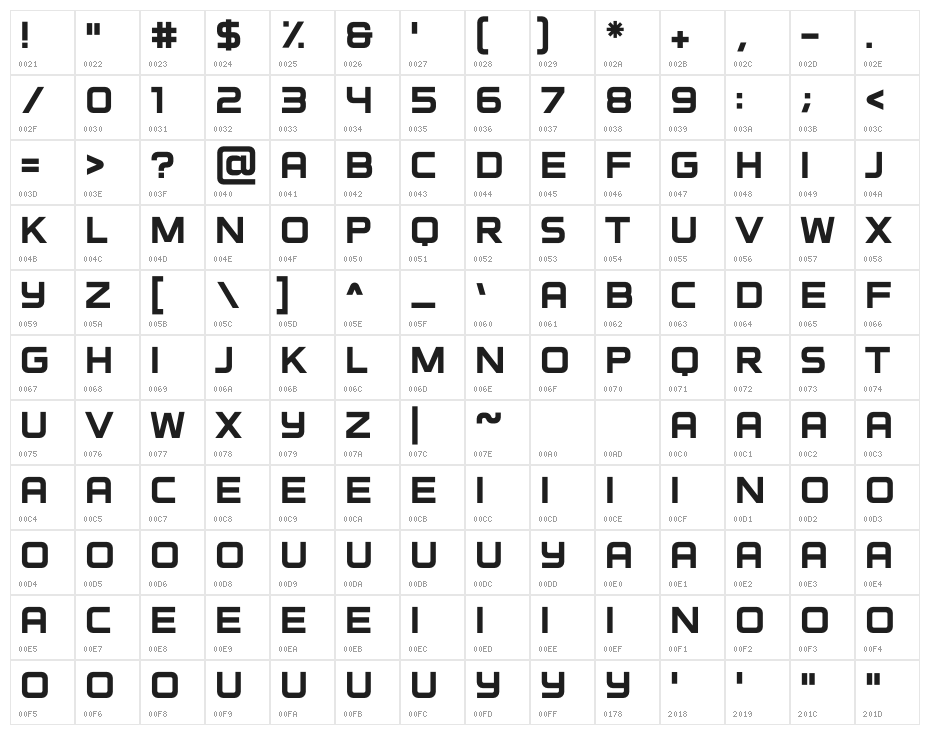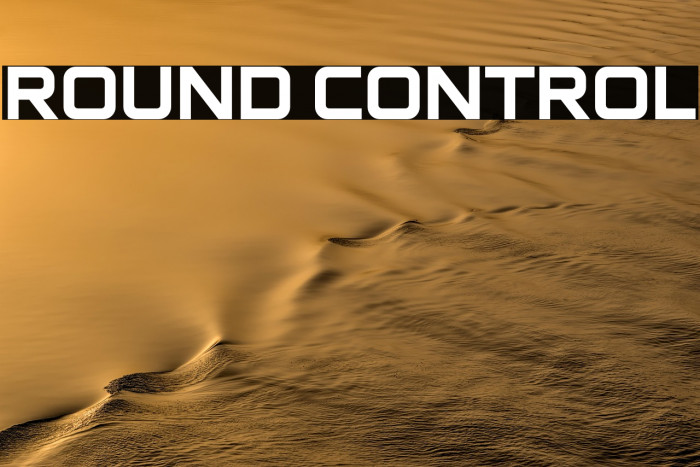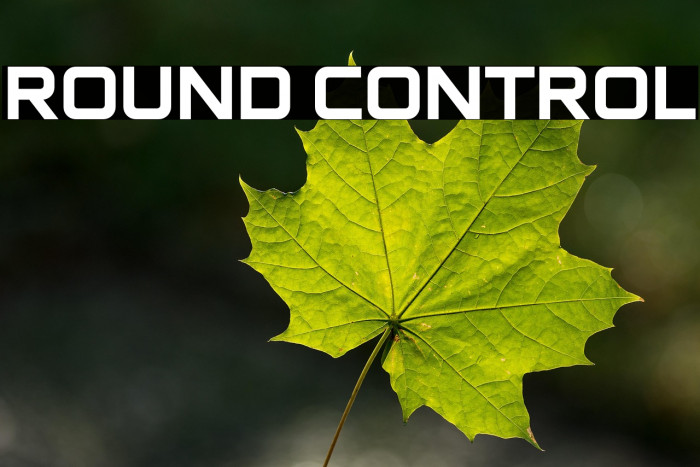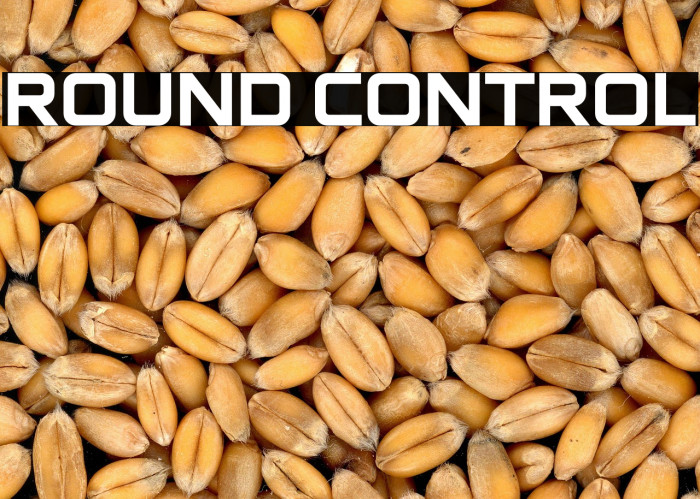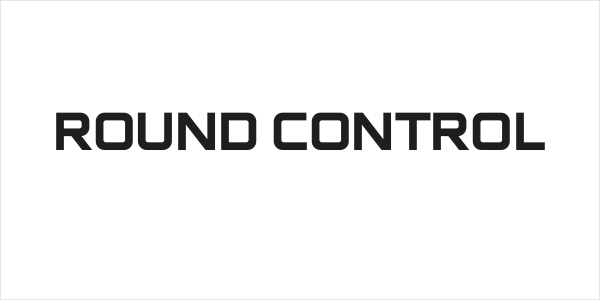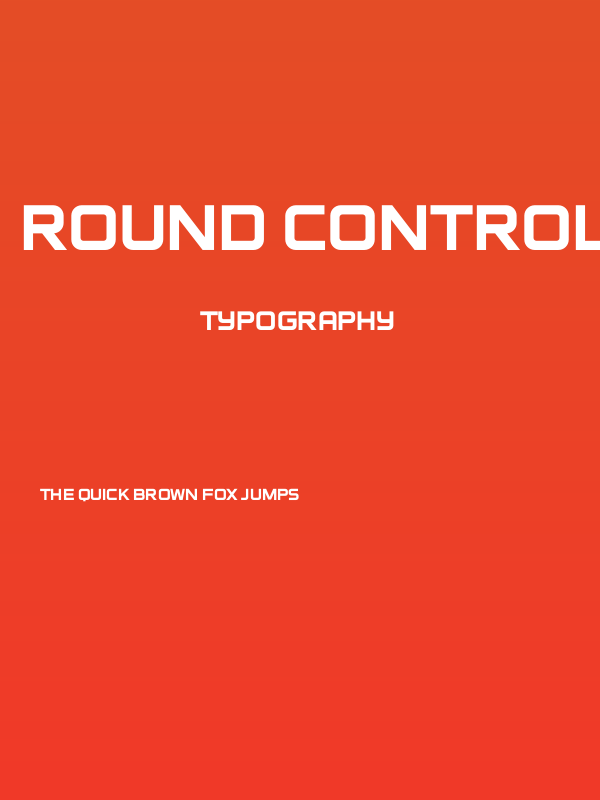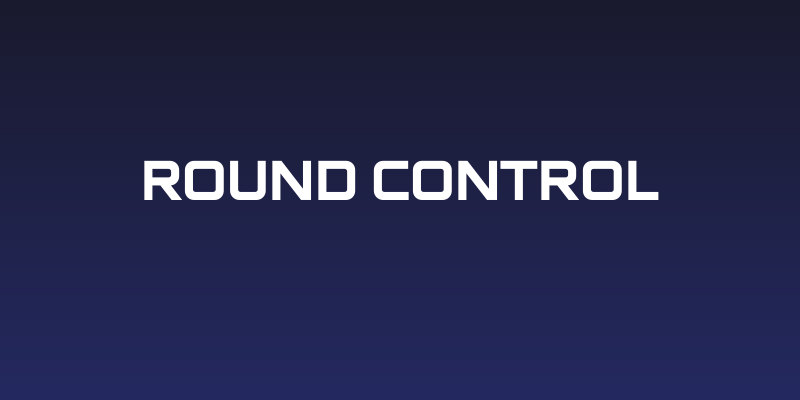
Round Control Font
| 使用场景 | Headlines, Logos, Digital Interfaces |
| 推荐项目 | Ideal for branding, advertising, digital interfaces, and modern print materials. |